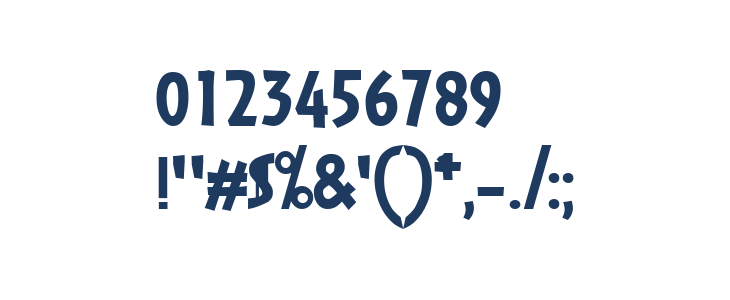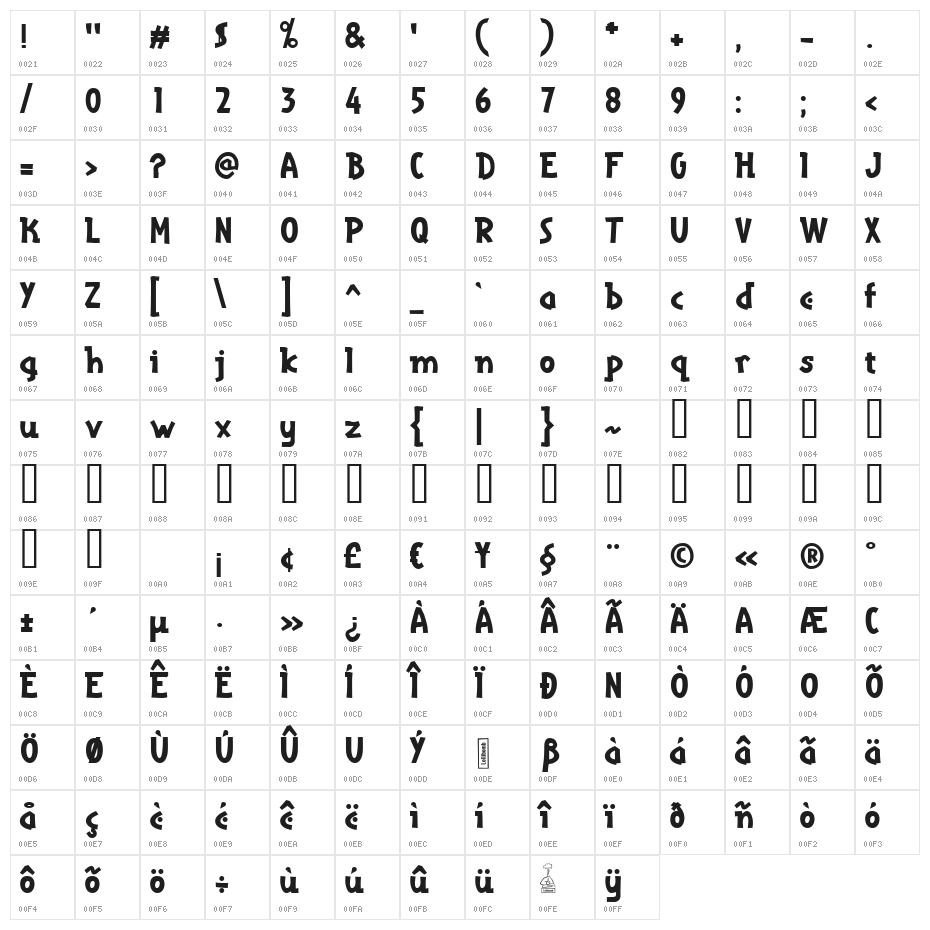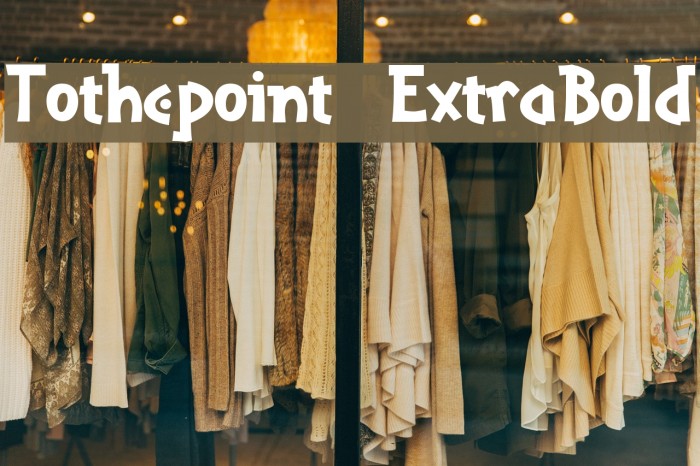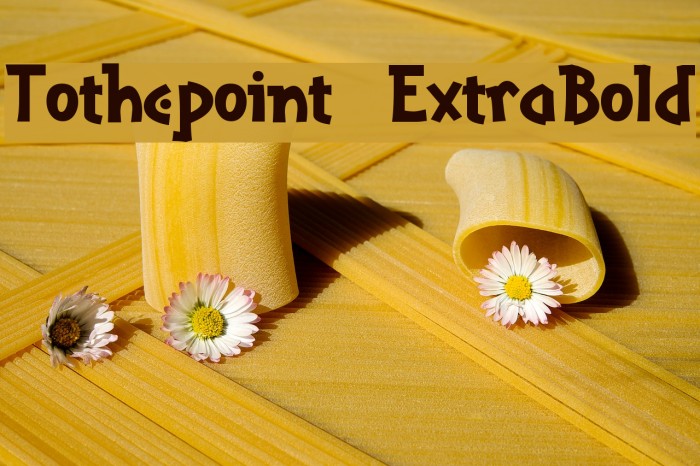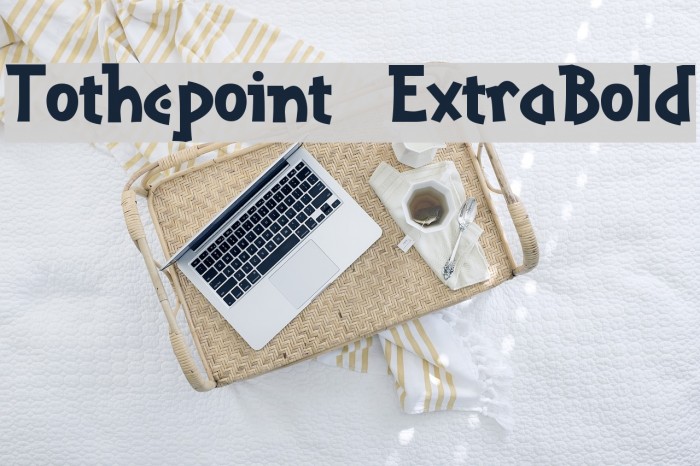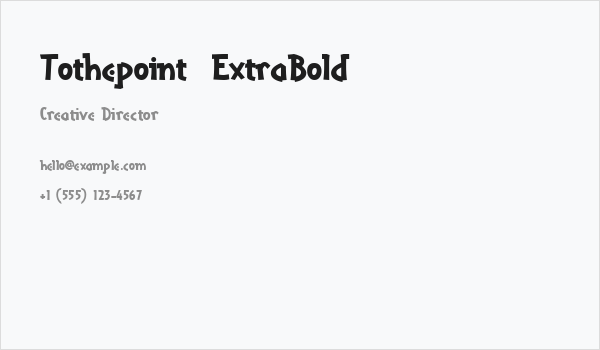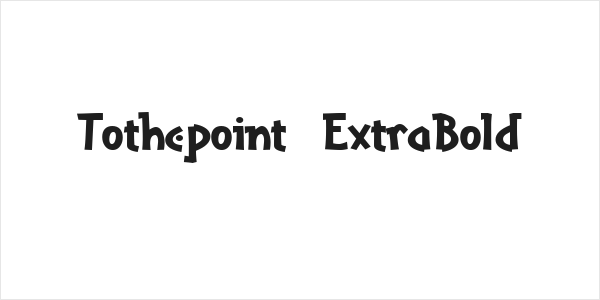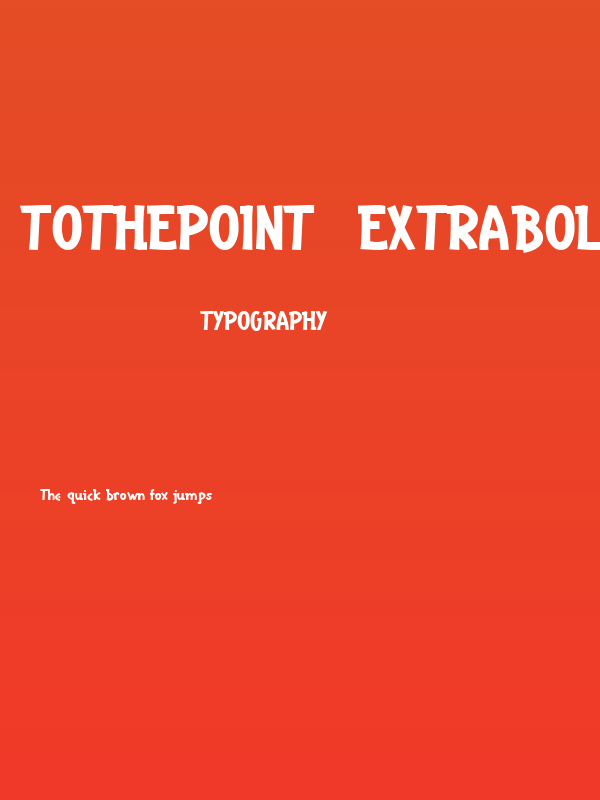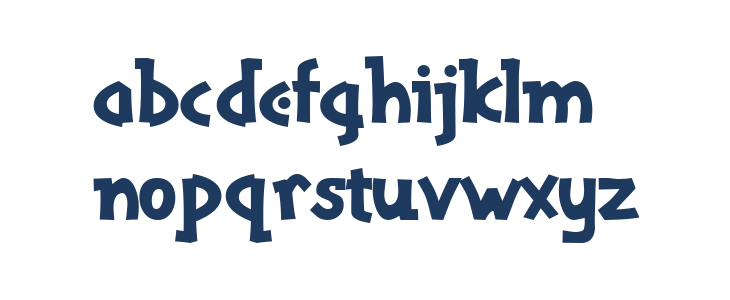
Tothepoint ExtraBold Font
| Stile generale | Playful, Whimsical |
| Progetti proposti | Ideal for children's books, playful branding, eye-catching posters, and creative advertising campaigns. |